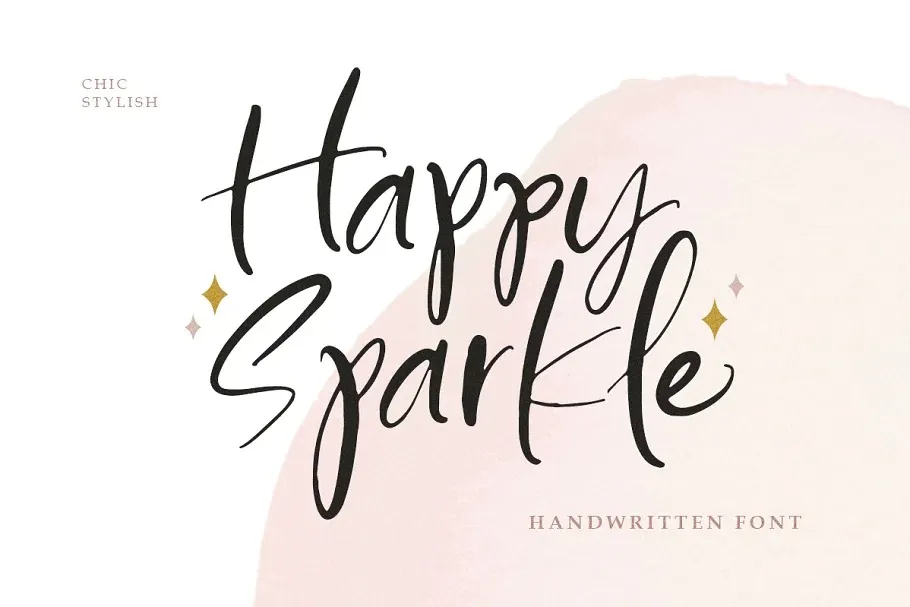
Happy Sparkle Font
A fonte ‘Happy Sparkle Font’ é uma opção perfeita para estilos criativos e divertidos, especialmente para designers que valorizam ambientes vibrantes e alegres. Esta é uma fonte script cheia de vida criada pelo Littlehand, adequada tanto para design empresarial quanto para criações casamentarias e anúncios de casamento. Ideal para personalizar logotipos, headlines ou até mesmo convites de casamento, esta fonte traz um toque positivo e alegre aos seus projetos, certamente deixando seu design brilhar com uma pitada de felicidade. Para aqueles que buscam uma fonte de escrita curvilínea para dar um toque especial em suas criações gráficas, ‘Happy Sparkle Font’ é definitivamente uma opção a considerar.